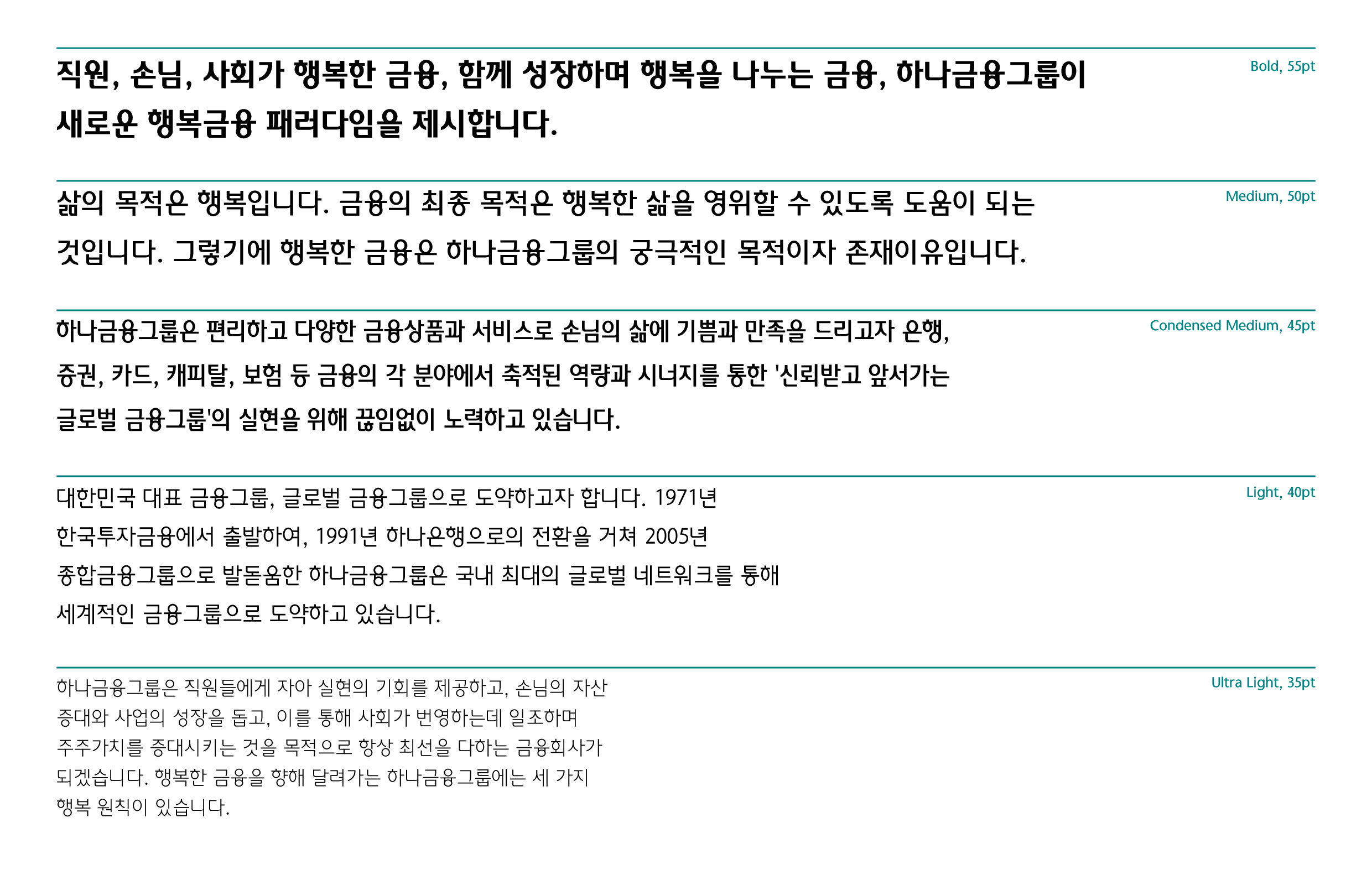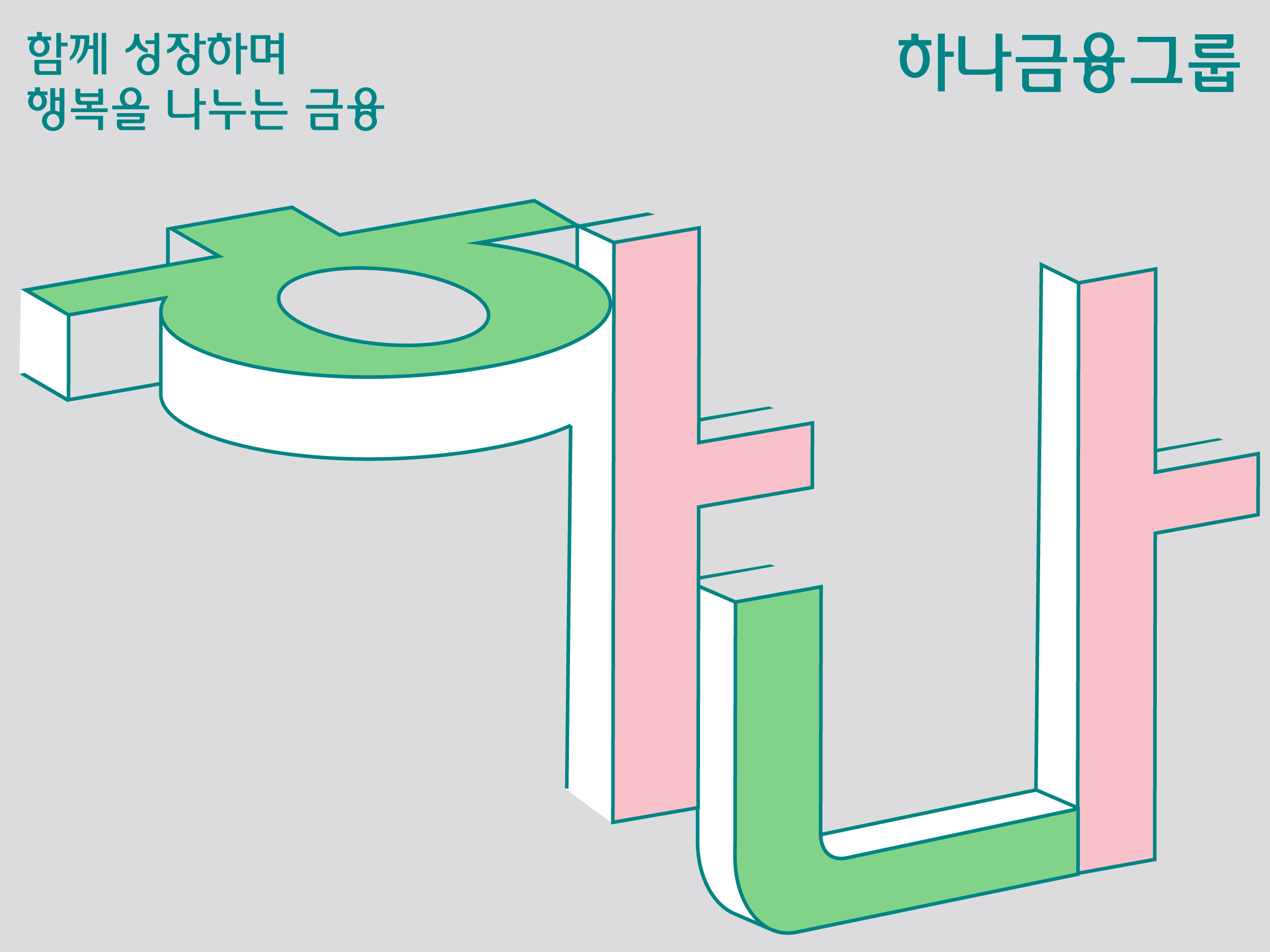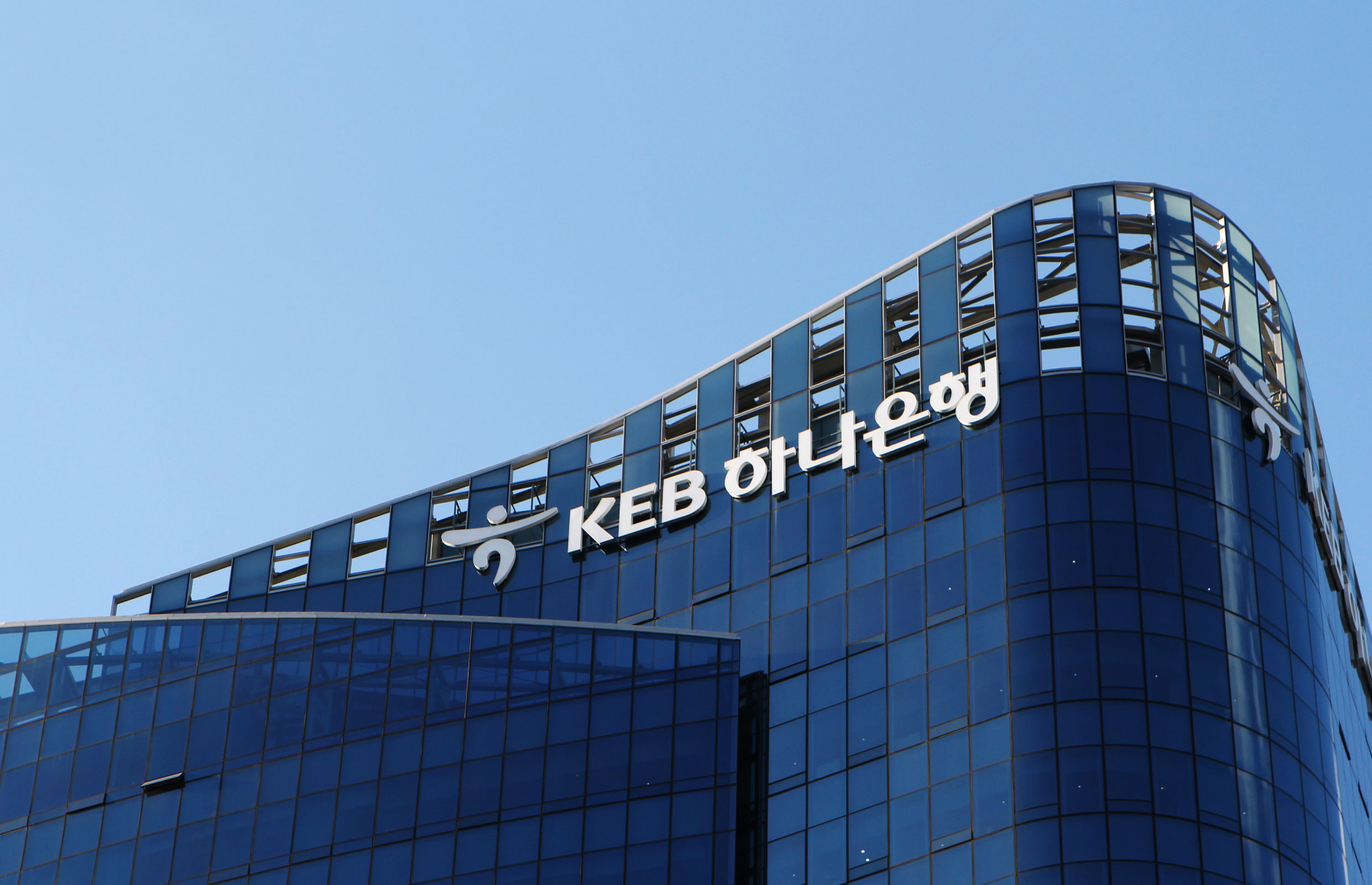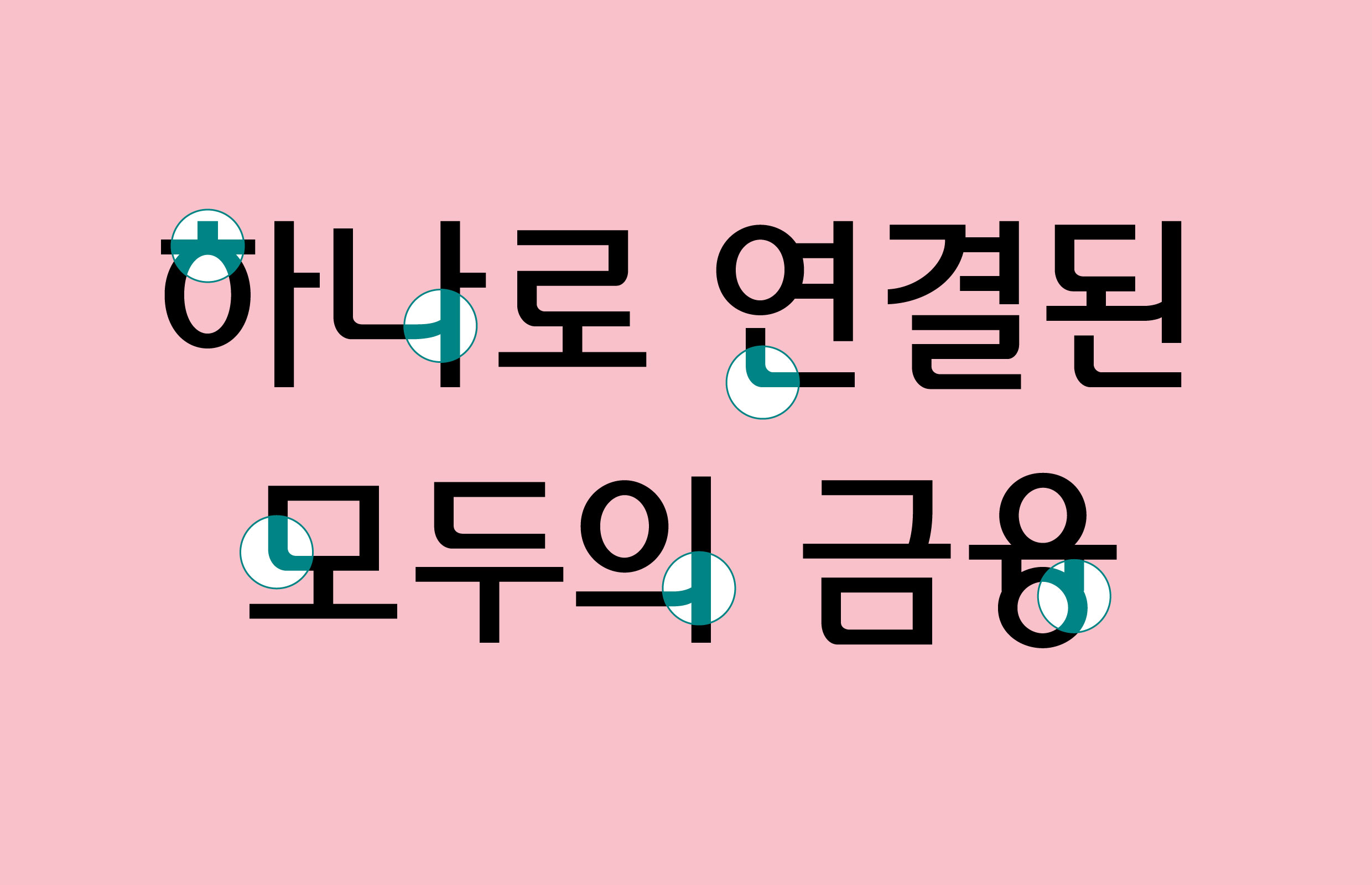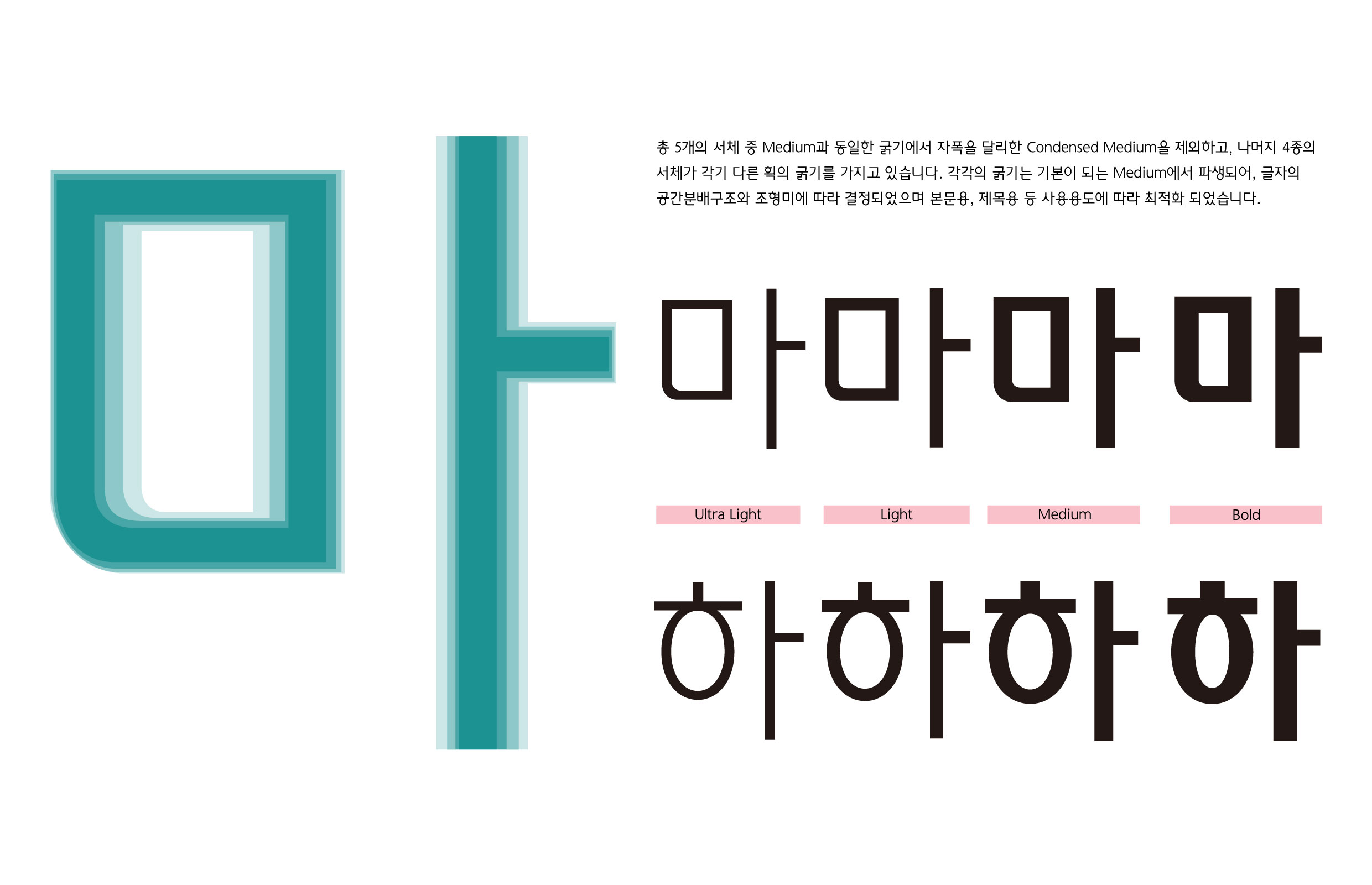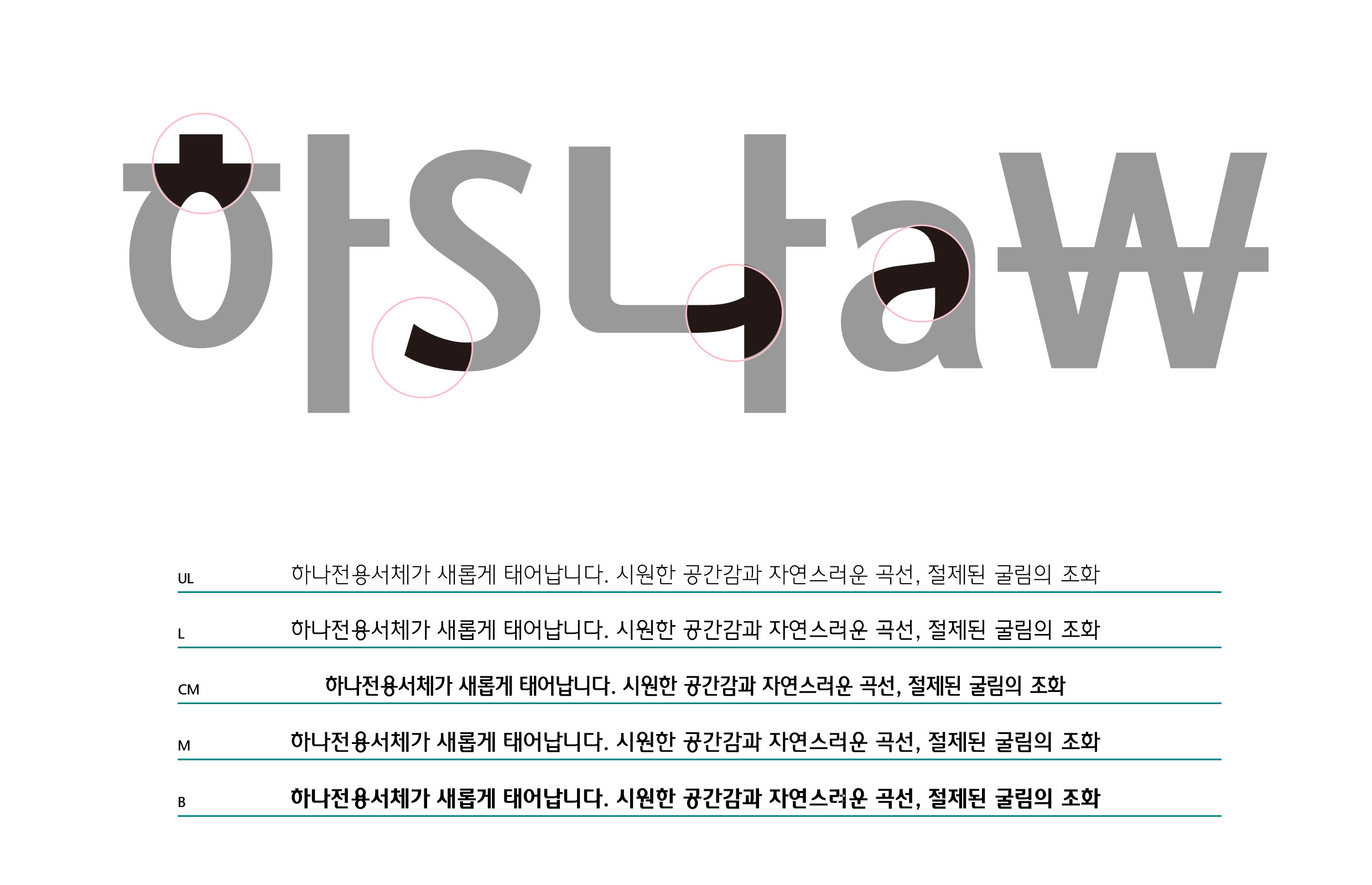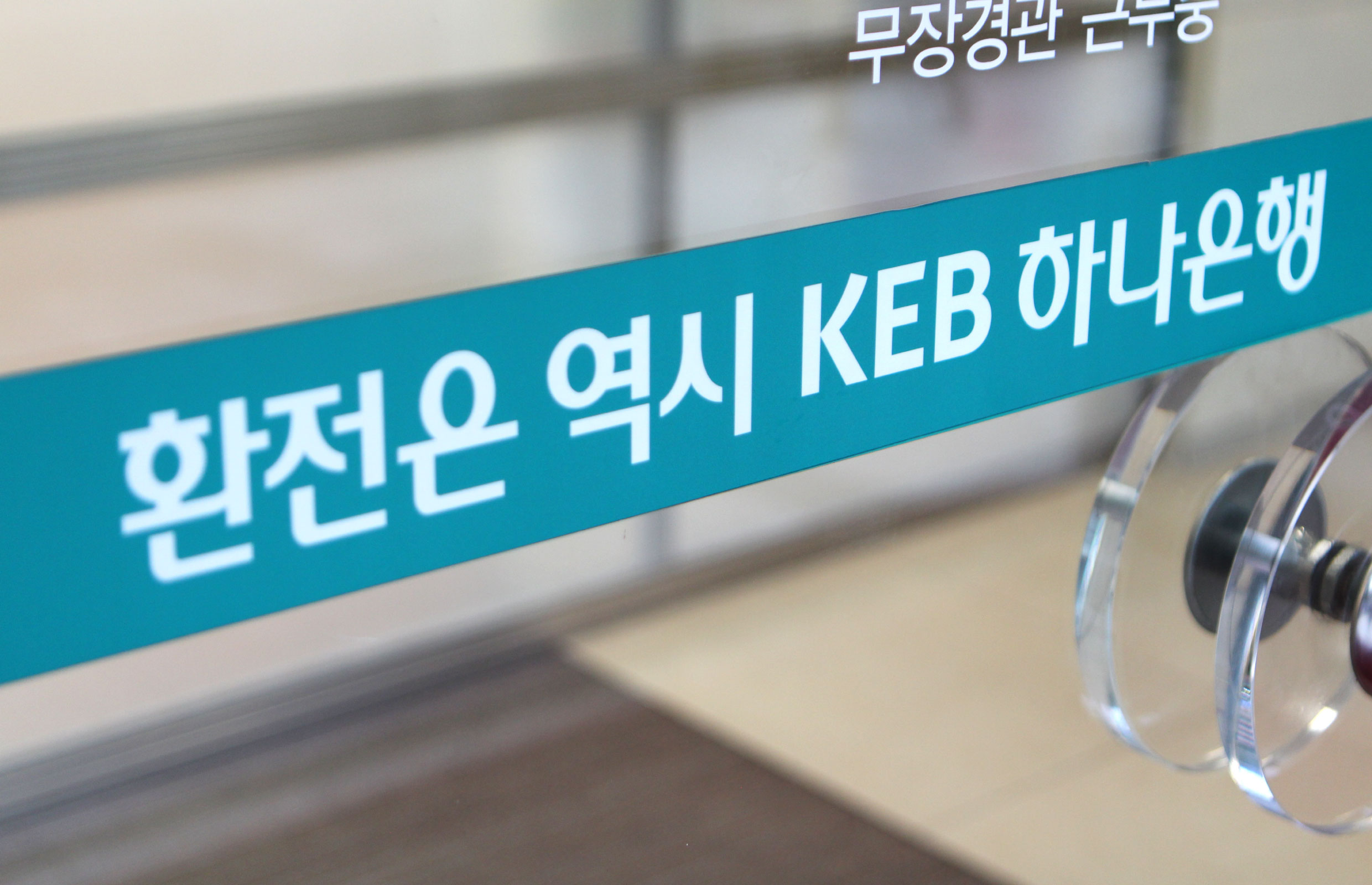
하나금융그룹
하나금융그룹 [하나체]
국내 은행권 최초의 금융그룹 전용서체. 광고 및 홍보물 외에도 그룹 내 임직원의 업무 환경에서 적극적으로 활용하기 위해 개발되었다. 하나금융그룹의 로고타입과 CI 형태를 기본 디자인 요소로 적용하였고, 젊고 신뢰감 있는 기업 이미지를 표현했다.